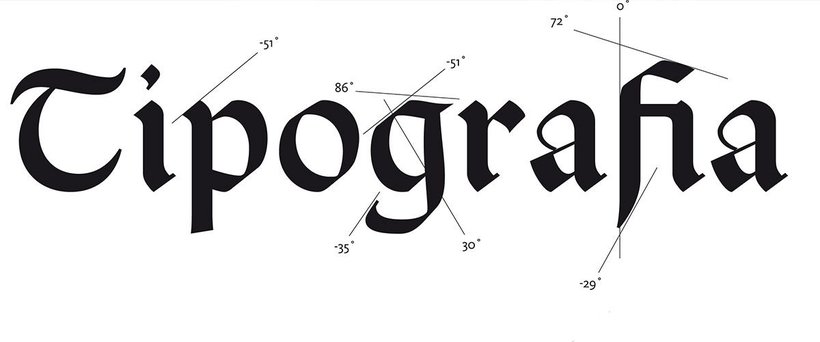
Tipografía: la voz de la marca
La comunicación en el diseño es visual, el mensaje se transmite por medio de imágenes y palabras y pueden ser literales o abstractas.
Aproximadamente un 80% de la comunicación es no verbal. Más que palabras, lo que realmente comunica es el lenguaje corporal, las expresiones, los gestos, las miradas, la entonación de la voz, la elección de las palabras. Muchas de las discusiones y mal entendidos que tenemos a diario surgen porque no nos comunicamos bien, yendo un poco más lejos, la mayoría de los problemas políticos internacionales tienen sus raíces en deficiencias en la comunicación.
El diseño gráfico es una herramienta que posee la humanidad para comunicar. La comunicación en el diseño es visual, el mensaje se transmite por medio de imágenes y palabras, que pueden ser literales o abstractas. ¿Existe una comunicación no verbal en el diseño gráfico?
La tipografía importa
En una pieza gráfica, una marca solo dispone de elementos visuales para intentar comunicar un mensaje y si el objetivo es seducir, convencer o ser categóricos con alguna idea, entonces debemos cuidar la comunicación no verbal de nuestra marca, es decir el uso del color, las imágenes, la composición, el tono con el que se dicen las cosas y de manera especial la tipografía.
La tipografía es la manera como las personas entienden la voz de una marca. Esta voz puede ser fría y sofisticada, o muy cercana como la de alguien con quien tienes confianza. Puede ser sólida y proyectar fortaleza. Una marca puede gritar tipográficamente, como las portadas de los diarios. Puede transmitir calma, dinamismo, rebeldía. La elección de la tipografía debería ser una tarea minuciosa, pues en un mundo donde todos tienen algo que decir, necesitas diferenciarte, alzar tu voz, pero sobre todo comunicar adecuadamente.
¿Cómo elegir bien?
Elegir una buena familia tipográfica es una habilidad muy requerida en un diseñador, se trata de una decisión de diseño que evidentemente afectará en la propuesta de identidad visual de la marca. Existen tres elementos fundamentales para elegir una tipografía: primero, el tipo de letra debe alinearse completamente a la identidad verbal de la marca, es decir la voz debe ser coherente con el uso de las palabras e imágenes. Segundo, la tipografía debe diferenciar a tu marca del resto, es una buena estrategia observar a los demás para comunicar diferente. Y por último, una buena tipografía debe ser capaz de conectar con la audiencia, invitar a ser leída, así como una buena voz pide ser escuchada.